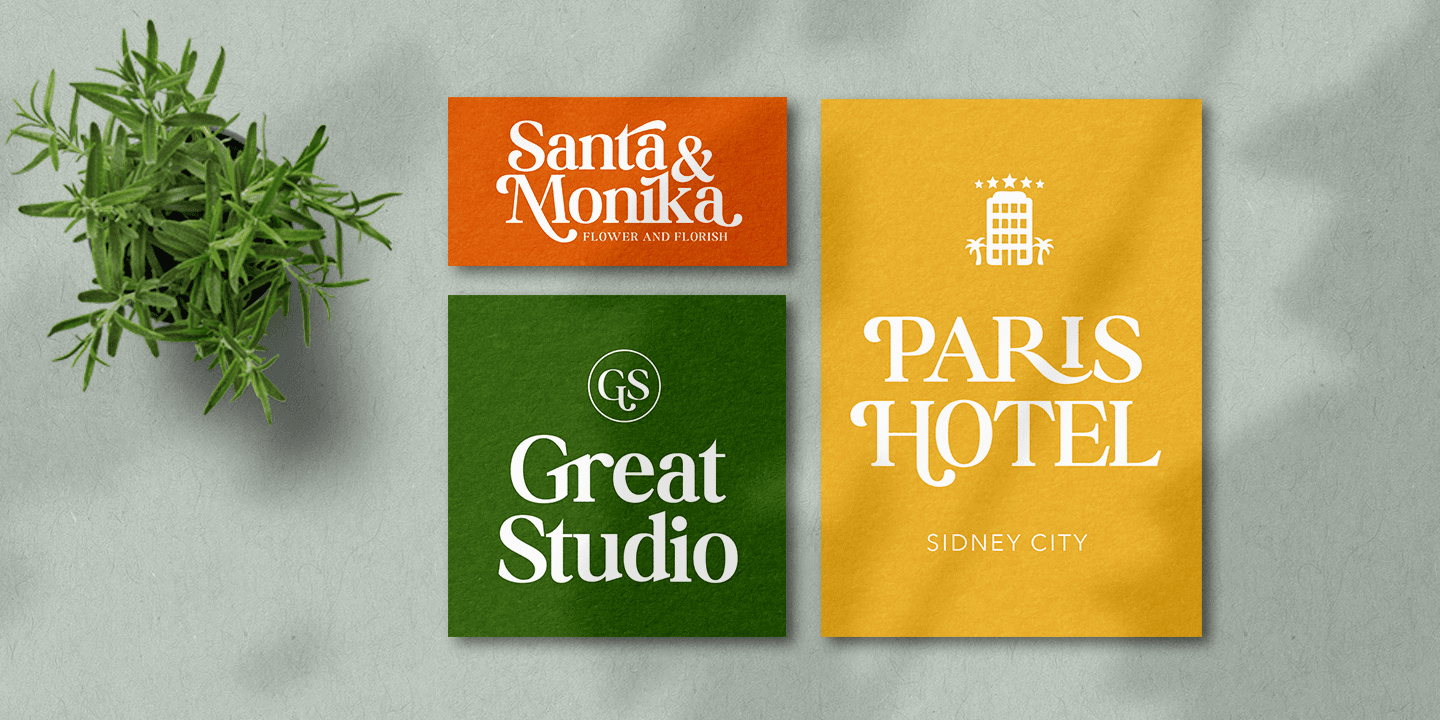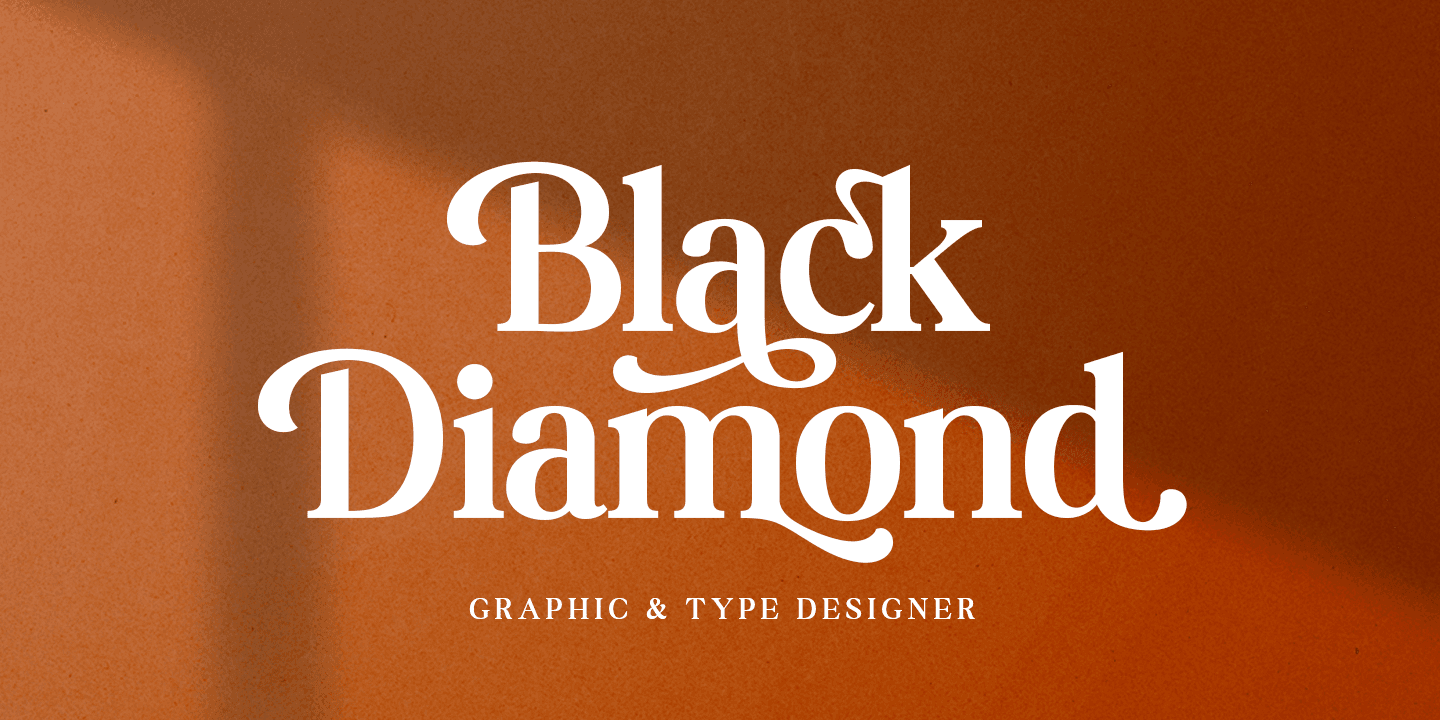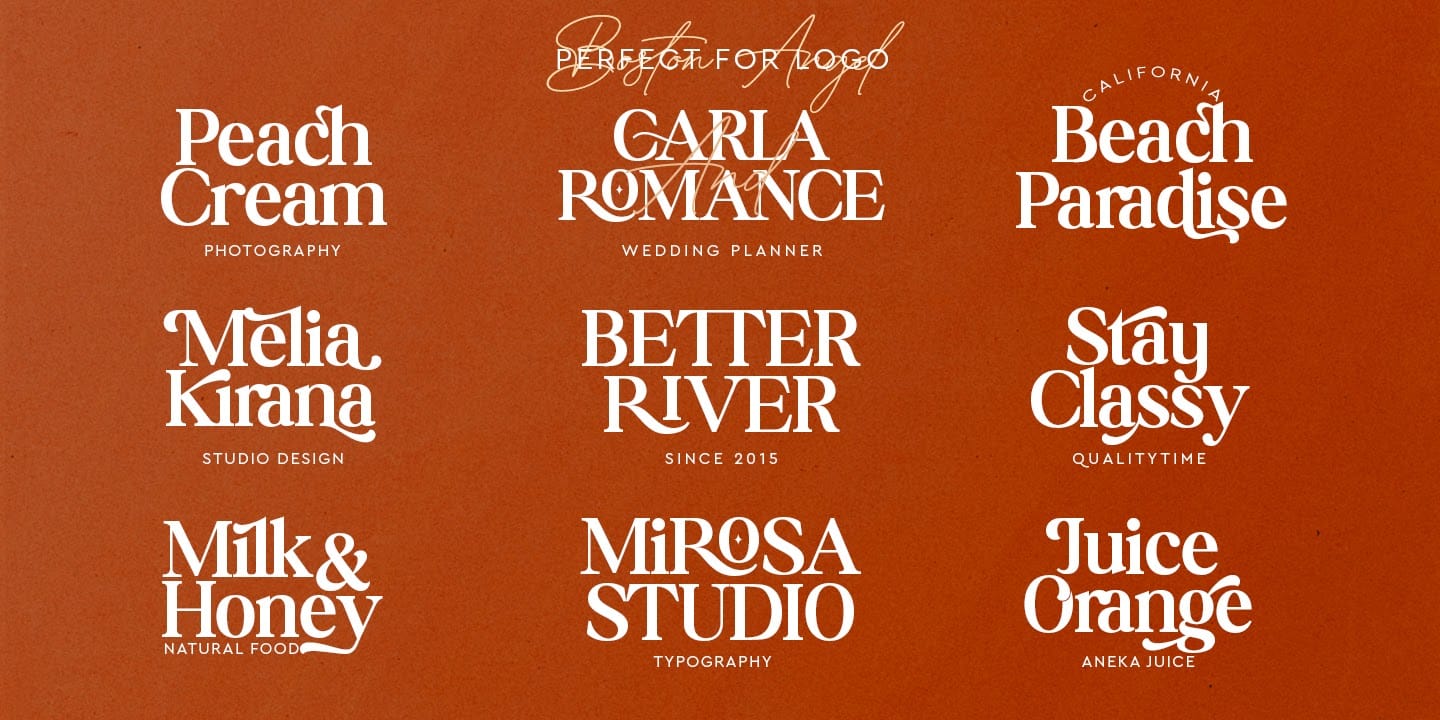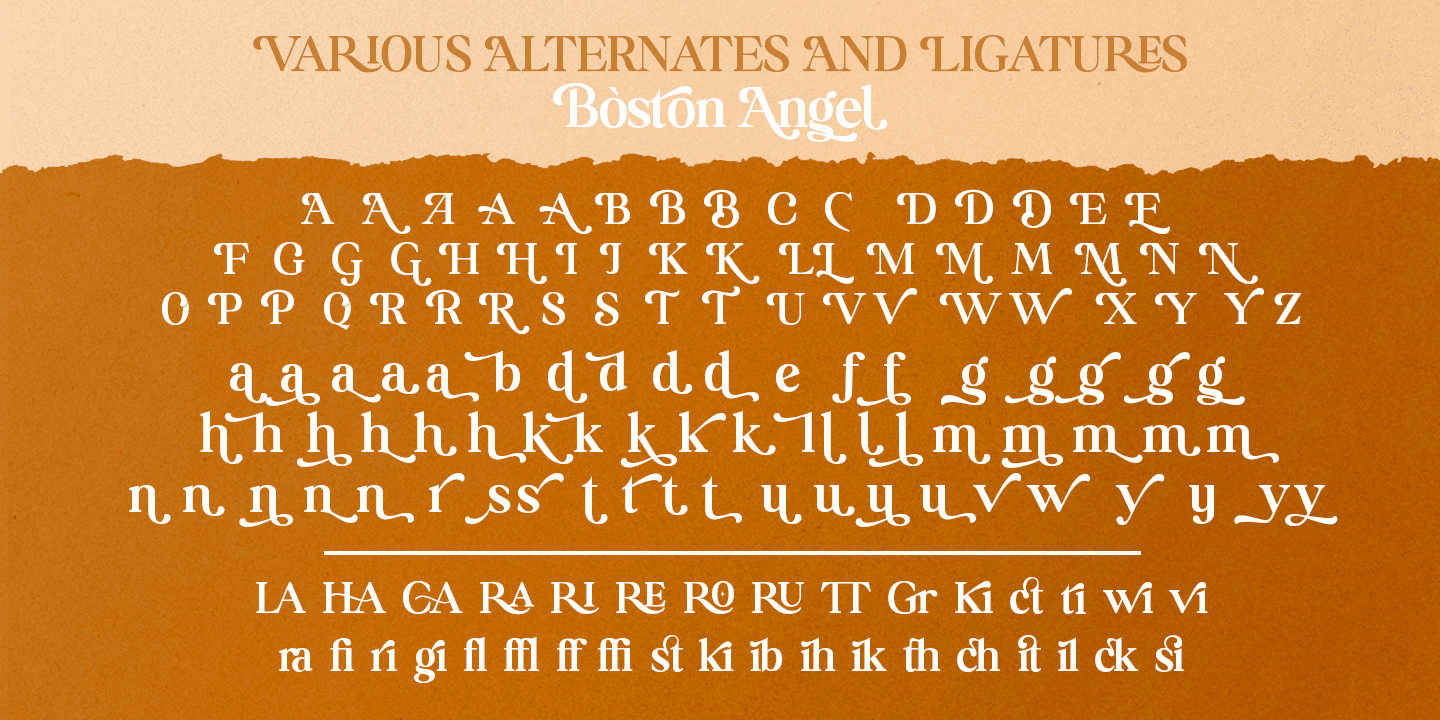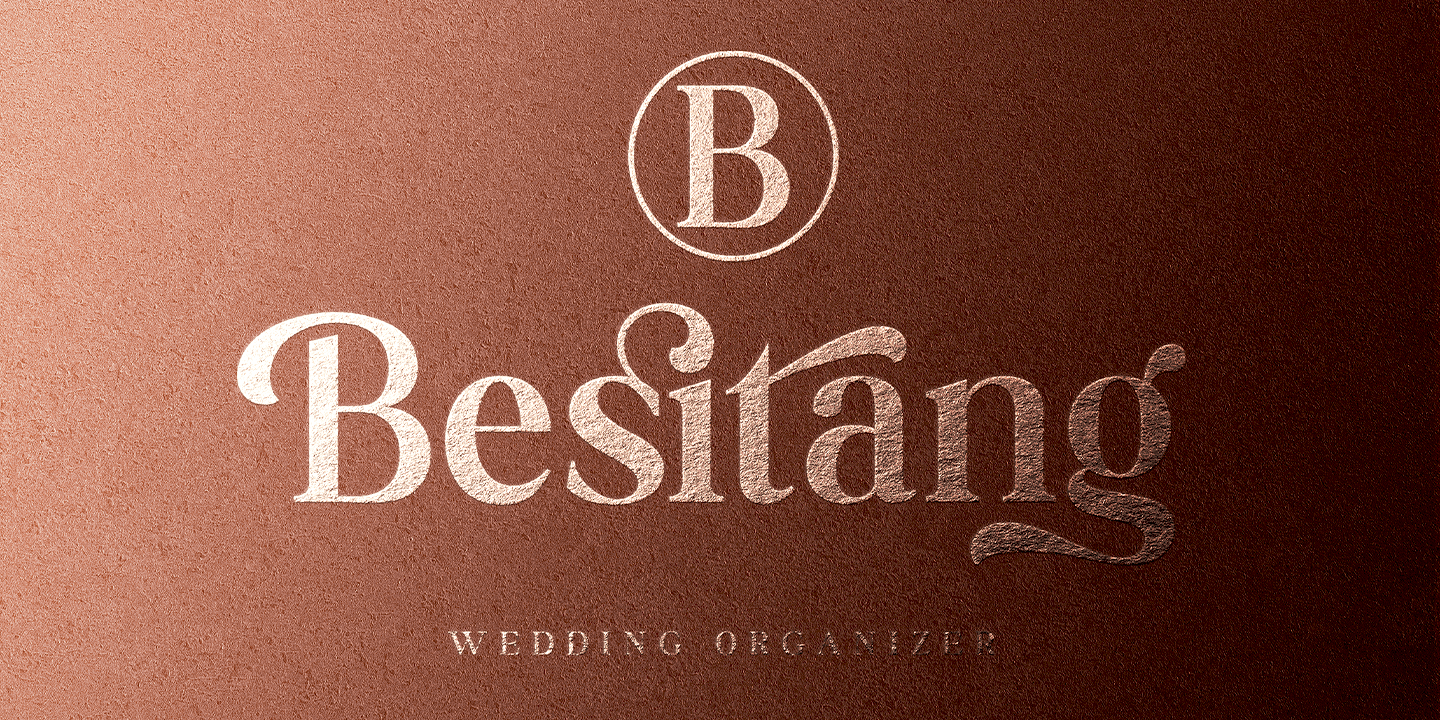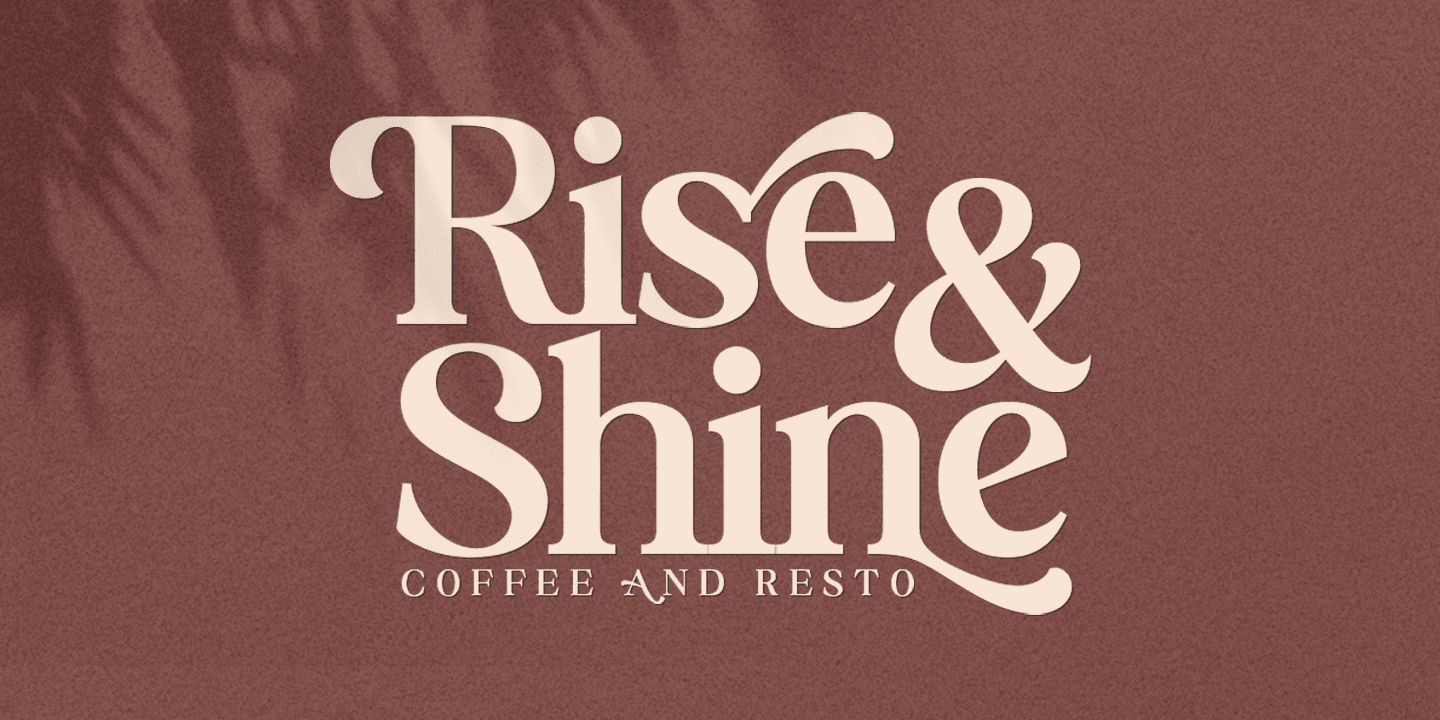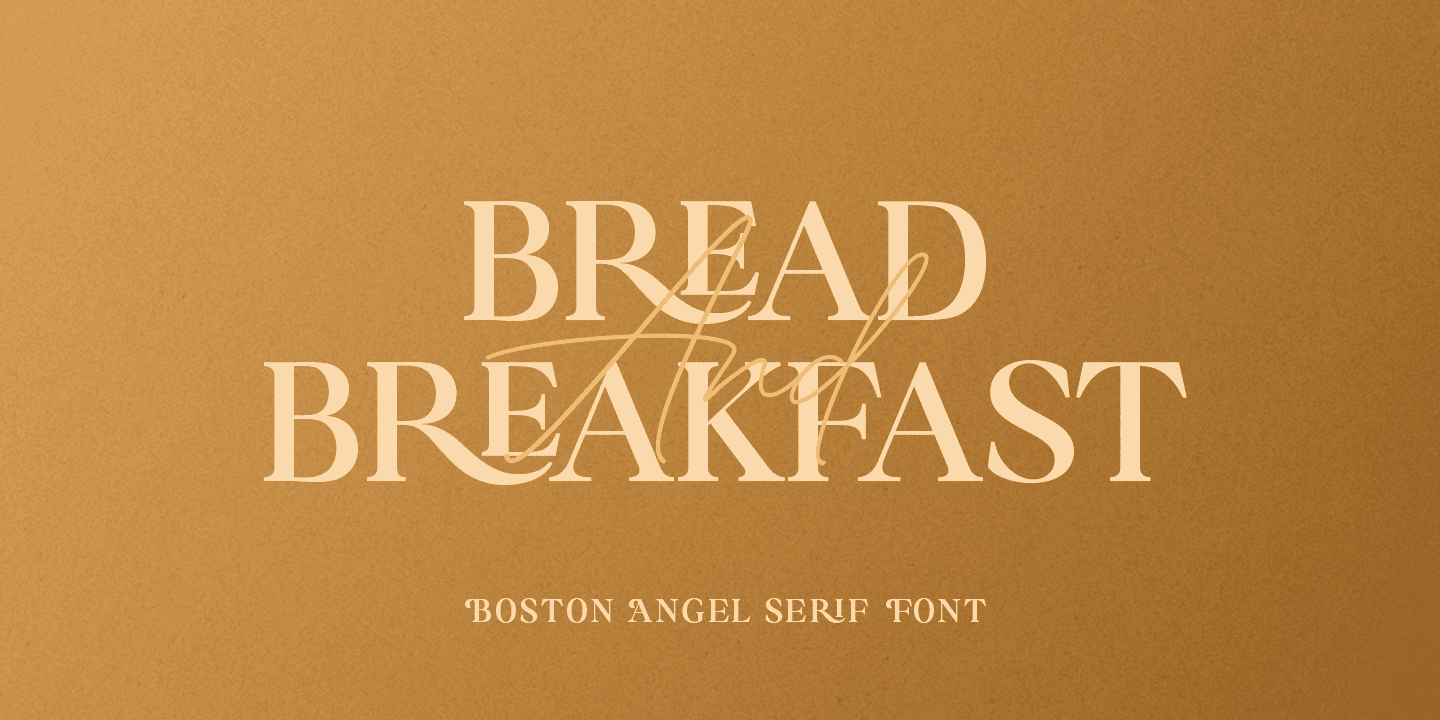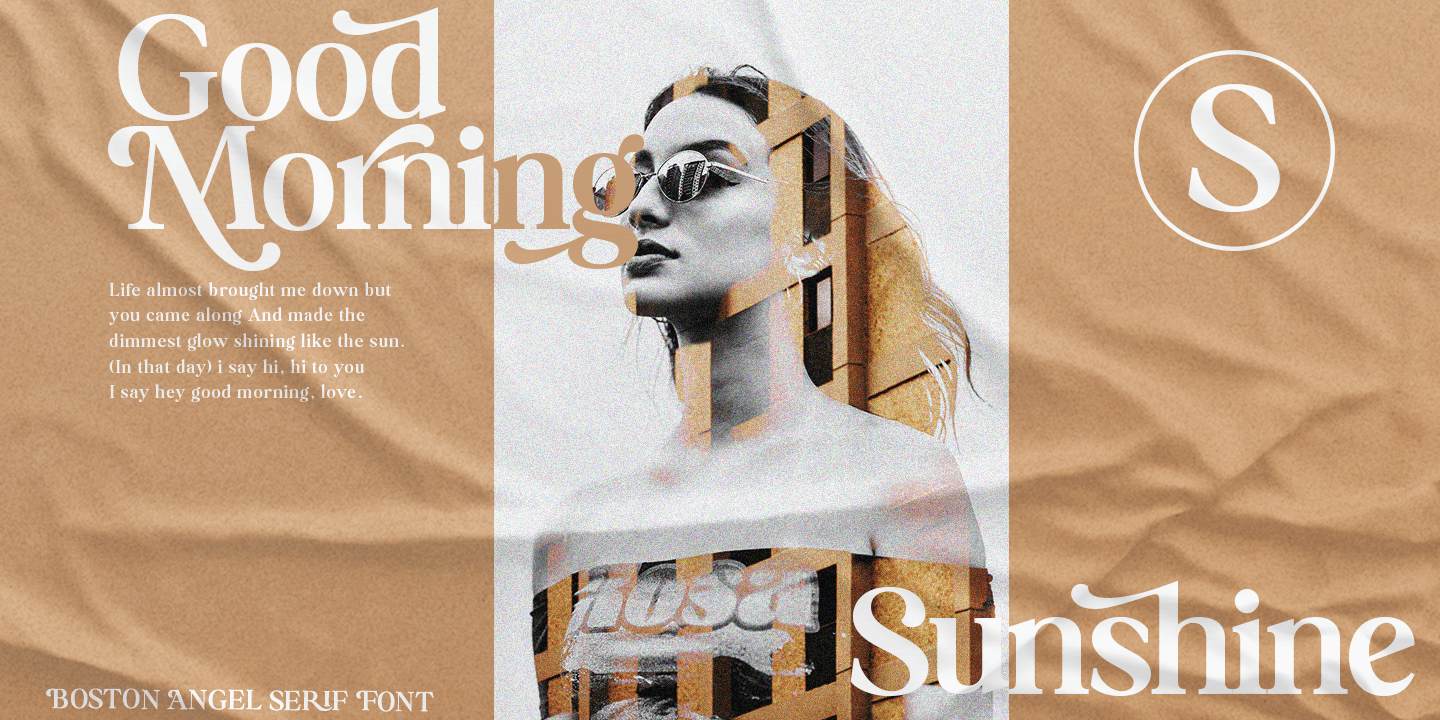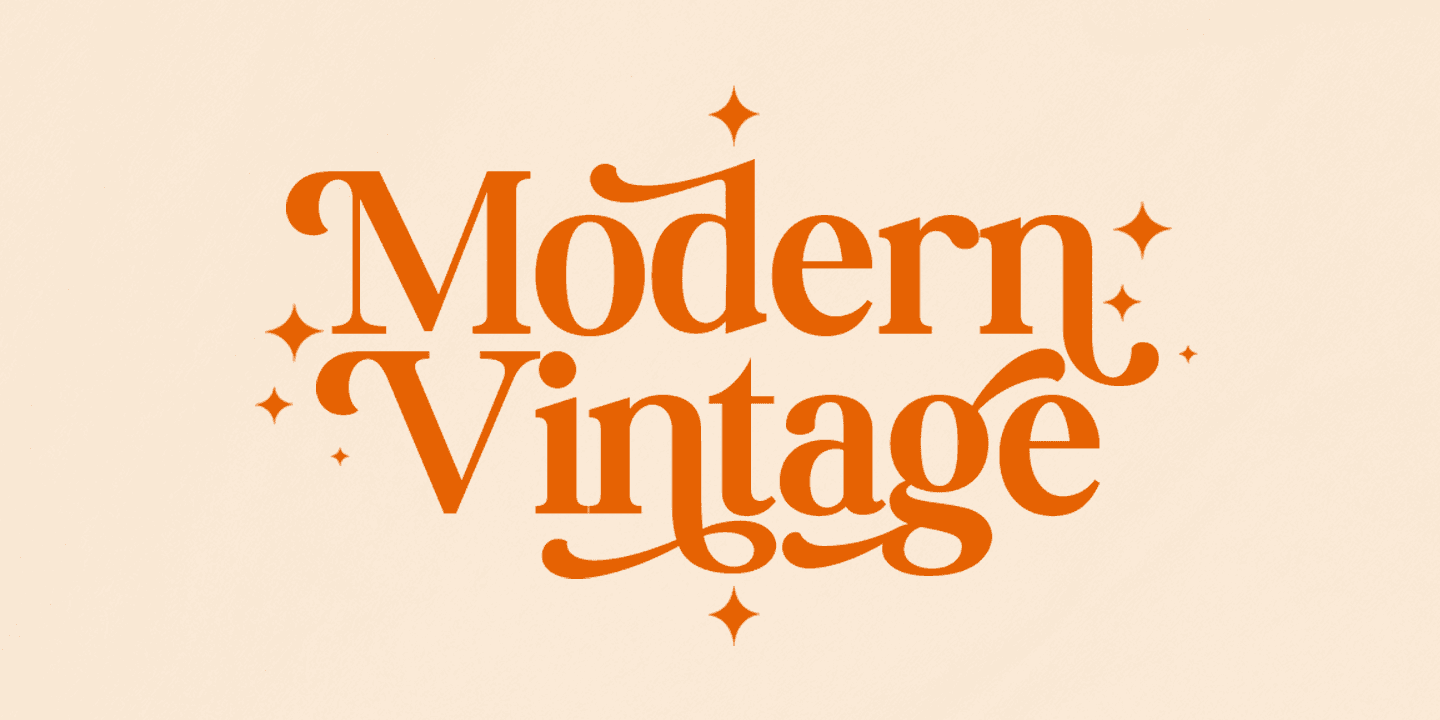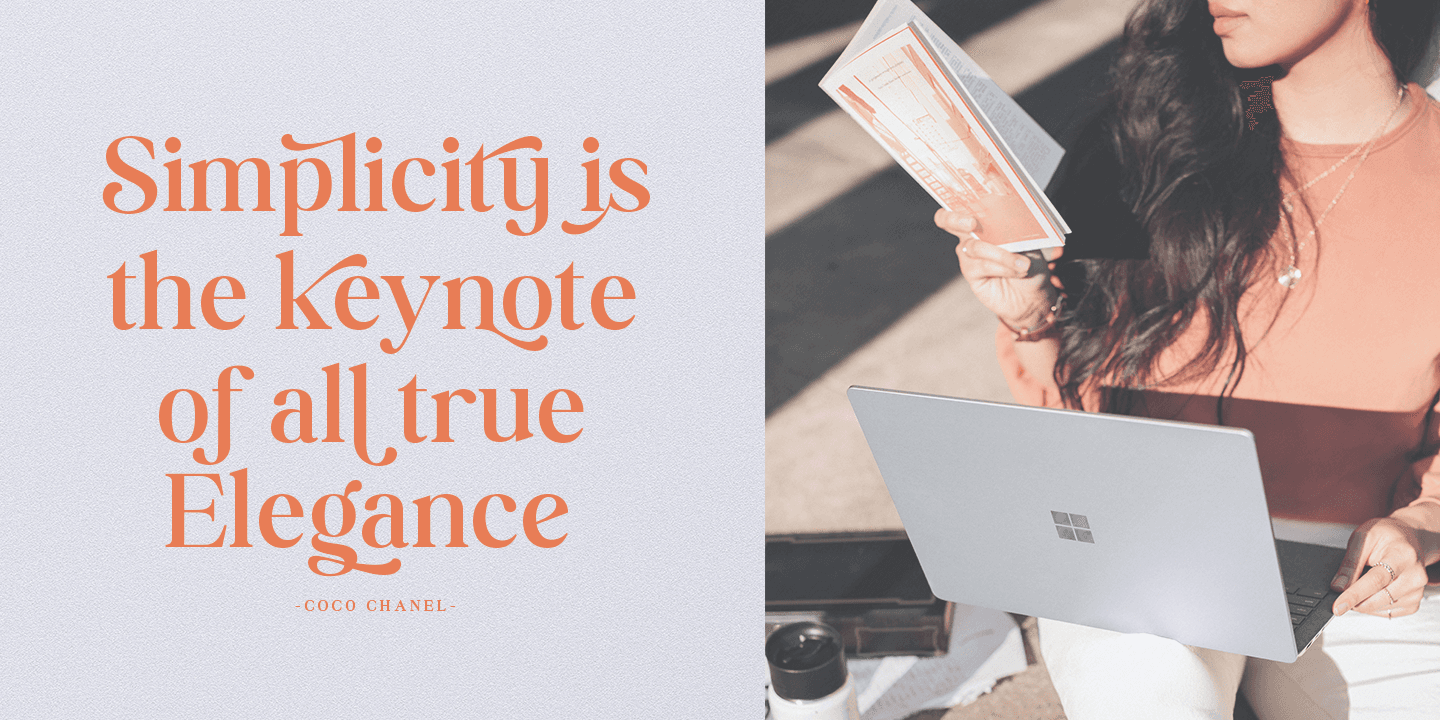
Boston Angel Serif là một font chữ serif cổ điển hiện đại được thiết kế theo phong cách hiện đại và sang trọng, hoàn chỉnh với quyền truy cập vào các tính năng OpenType của bạn để truy cập vào một loạt các chữ cái và chữ ghép thay thế, lựa chọn các chữ cái bạn thích từ các biến thể của chữ hoa và chữ thường để có được những thiết kế sang trọng và trang nhã. Bộ font Boston Angel Family độc đáo và linh hoạt với 35 chữ ghép và 114 lựa chọn thay thế để làm đẹp cho thiết kế bạn thích. Font chữ này hoàn hảo cho các dự án xây dựng thương hiệu, thiết kế Logo, Thương hiệu quần áo, bao bì, tiêu đề tạp chí, quảng cáo, áo phông, bưu thiếp và hơn thế nữa.
• Boston Angel Thin
• Boston Angel Light
• Boston Angel Regular
• Boston Angel Medium
• Boston Angel Bold